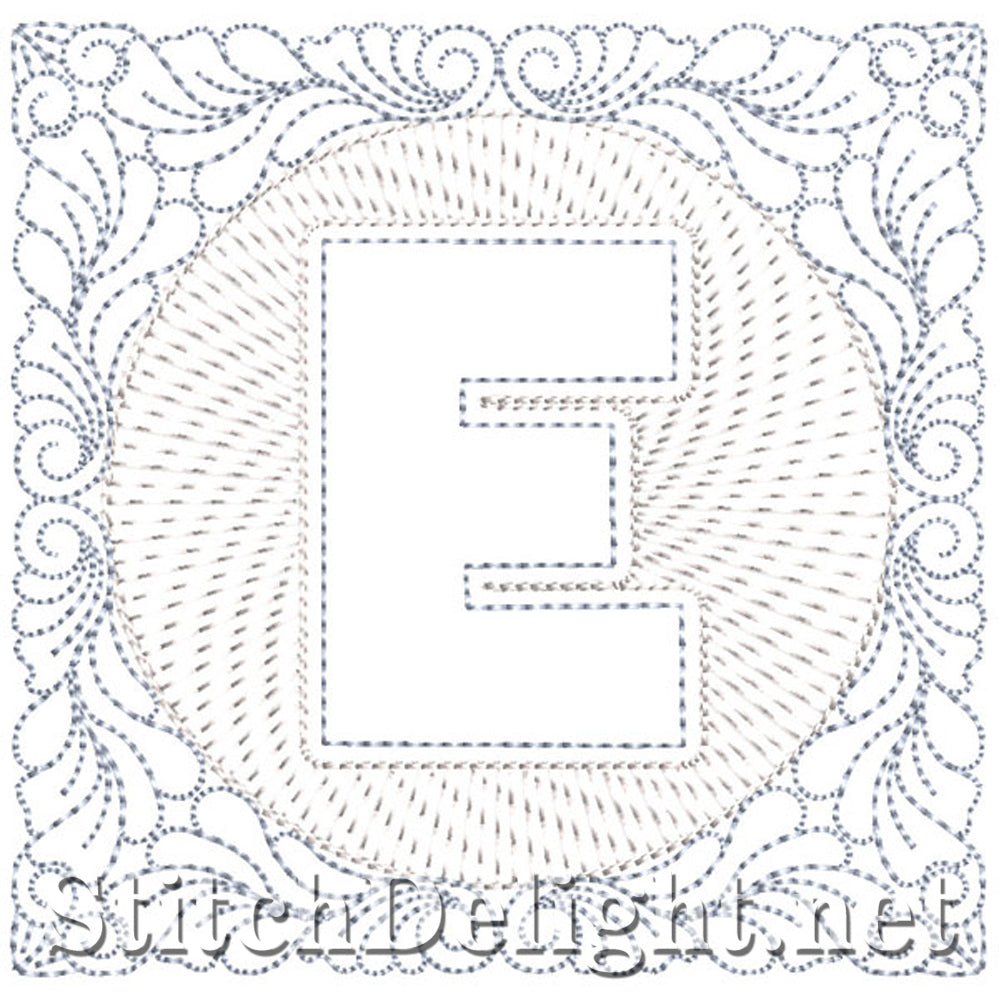
SDS1185 Quilters Bloklettertype E
Dit prachtige lettertype ziet er prachtig uit wanneer het wordt gestikt op een sandwich van weggesneden, tussenvulling en stof - stretchstof geeft een prachtige hoge loft - spel een naam of maak een alfabetquilt - Deze worden gedaan in de 4x4 hoepel (u kunt vergroten naar believen) De blokgrootte is 3,74x3,74" en het aantal steken ongeveer 6600 steken